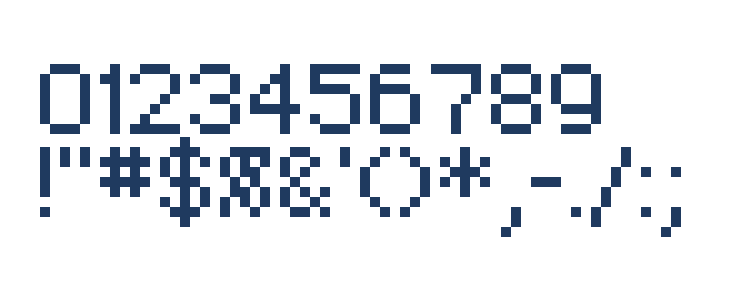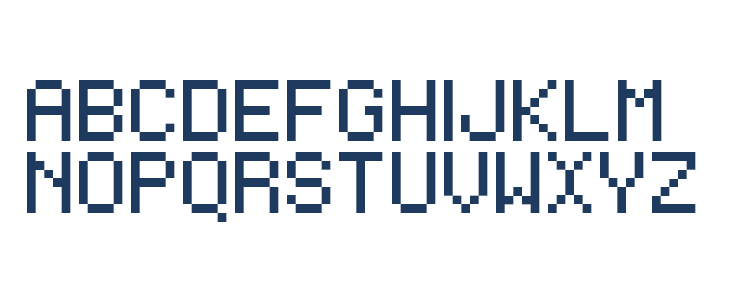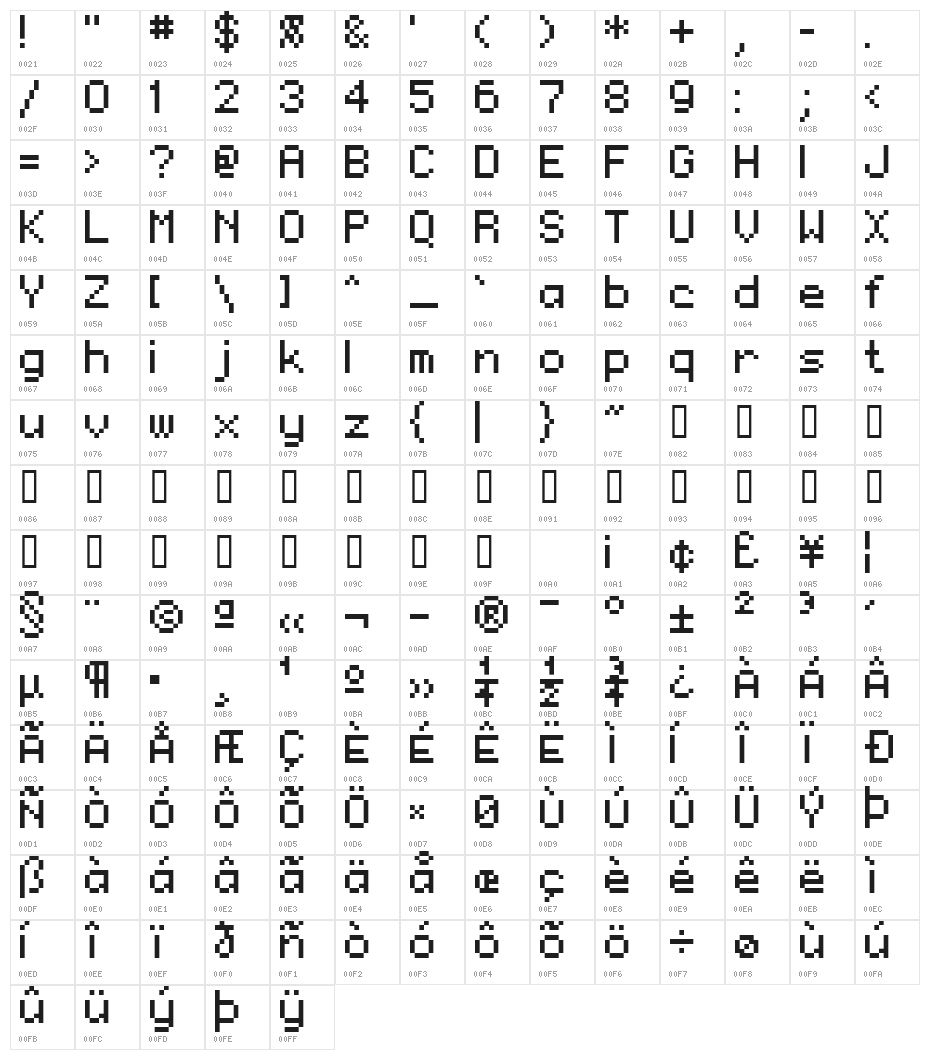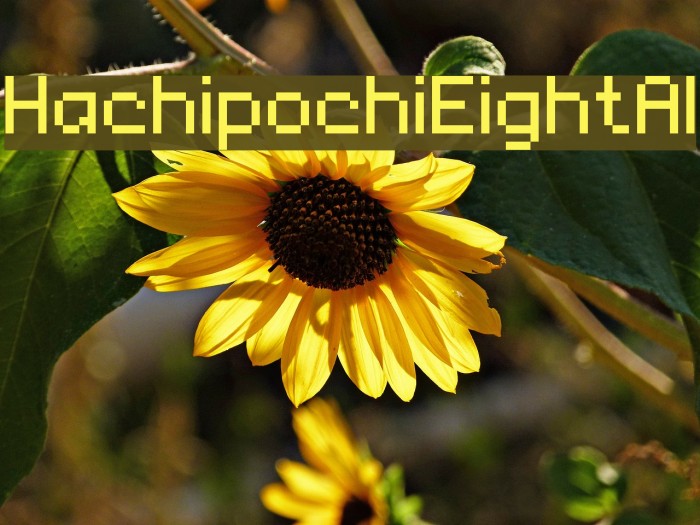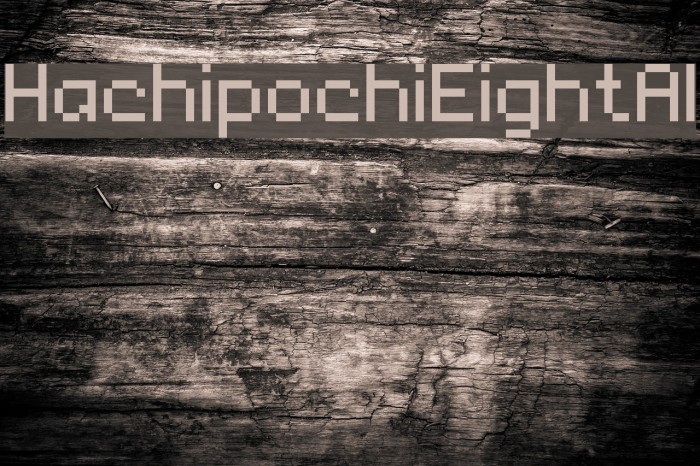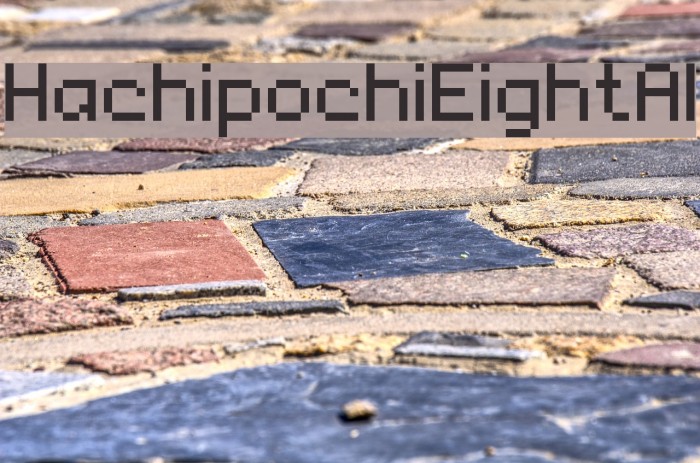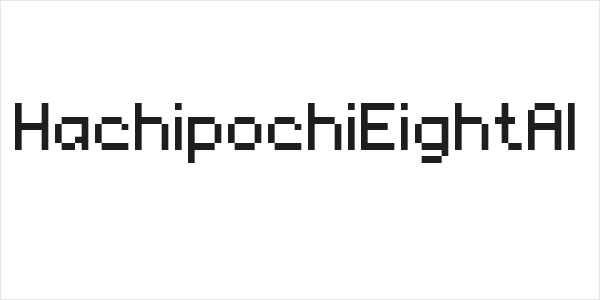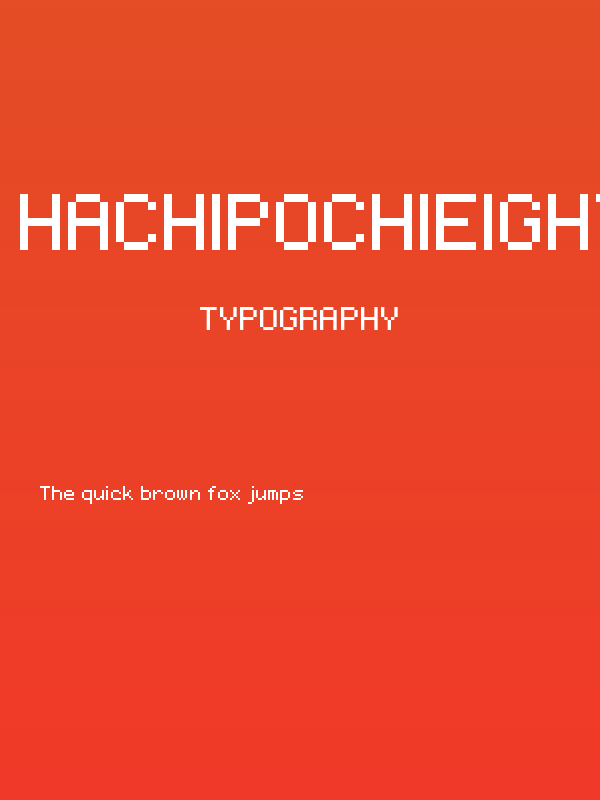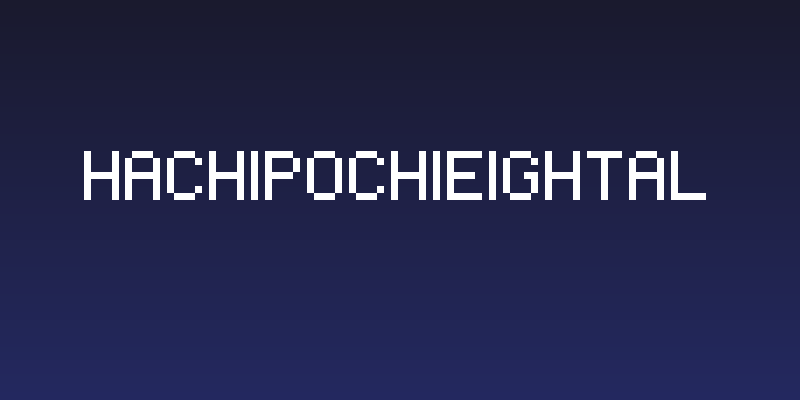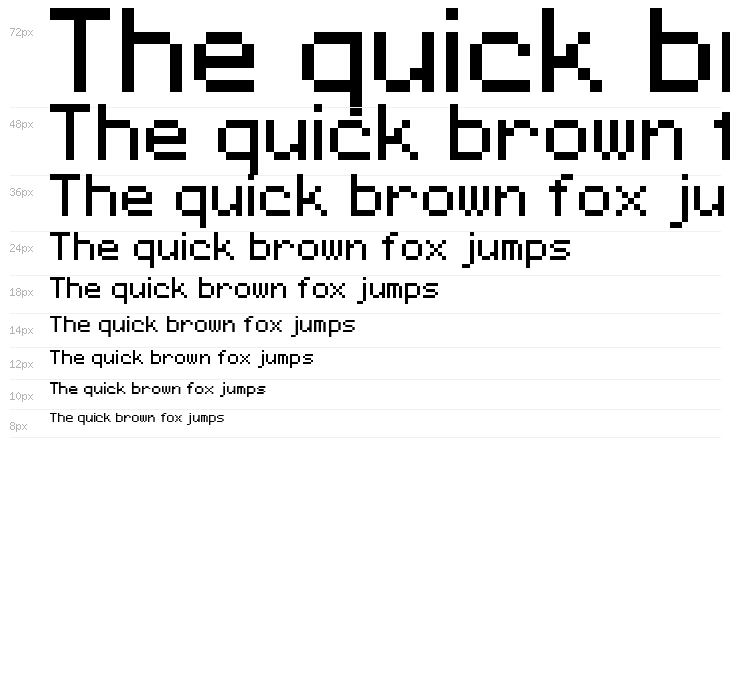
HachipochiEightAl Font
| Caso d'uso | Headlines, Logos, Digital Art |
| Progetti proposti | Ideal for video game design, retro-themed posters, digital art projects, and any creative work that seeks to evoke a nostalgic digital feel. |